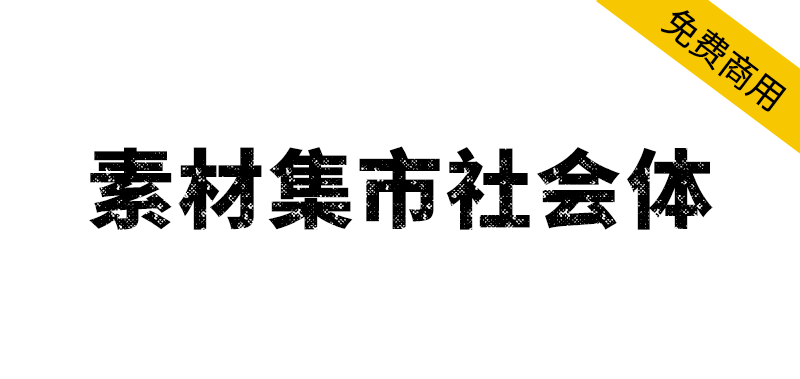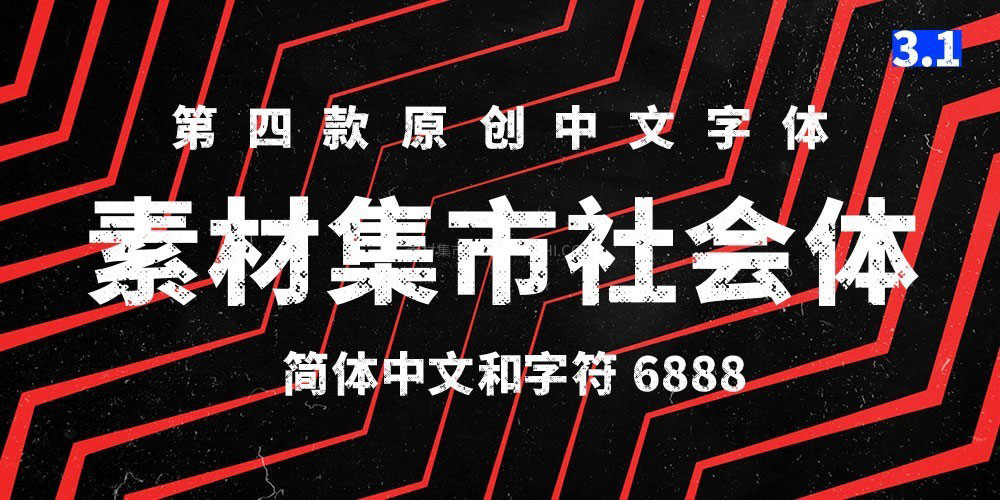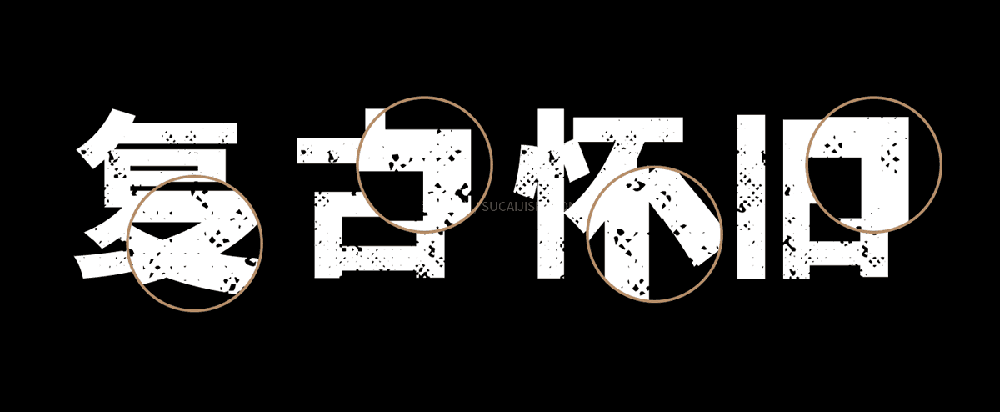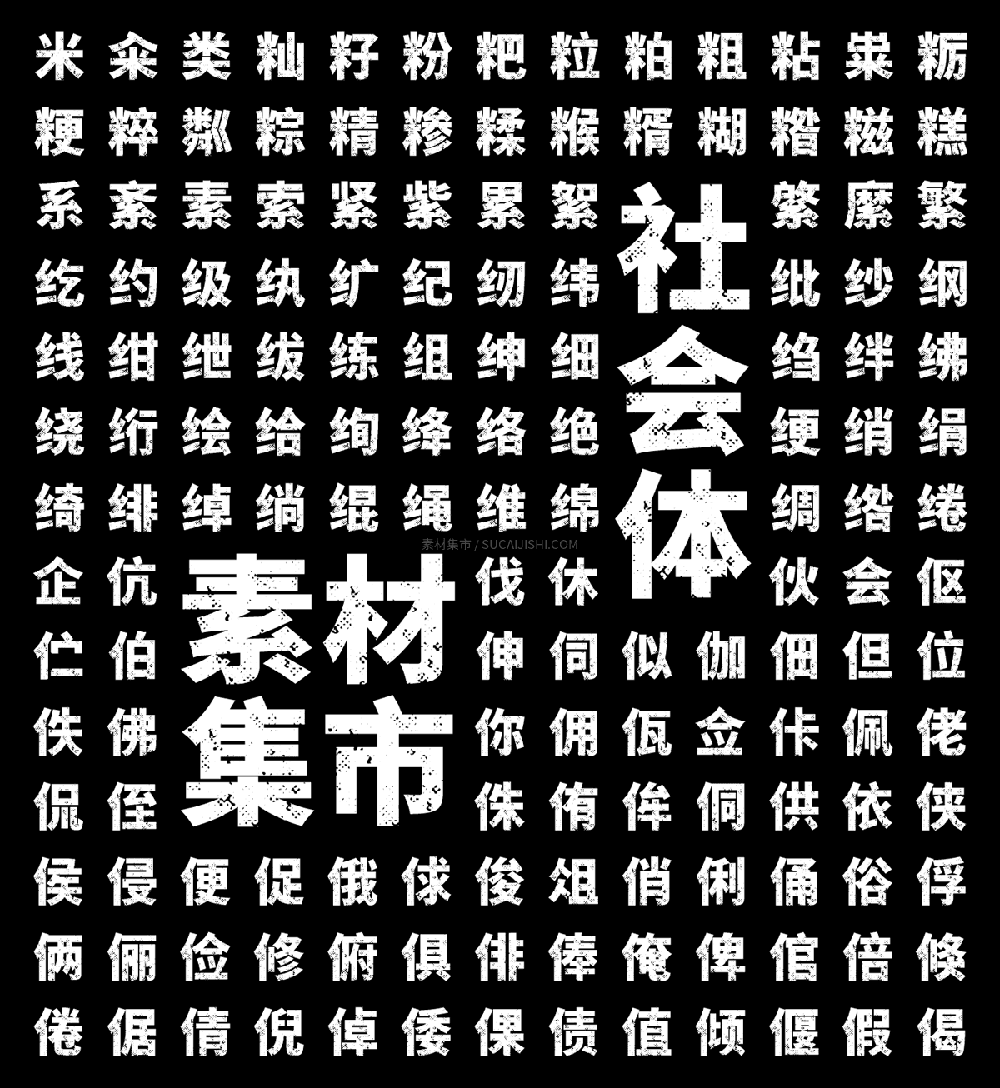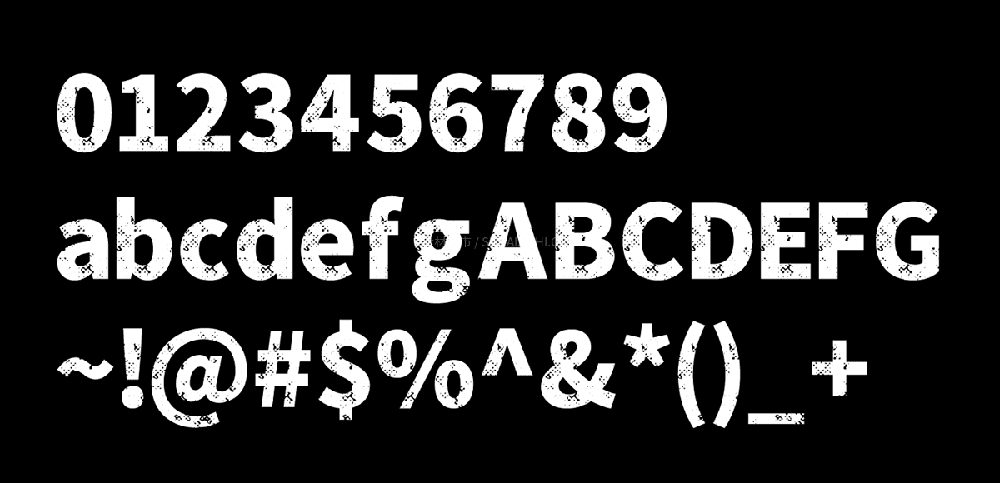
素材集市社会体是素材集市第四款原创字体「社会体」,由10名字集成员近4个月时间联合制作完成。作为各行业设计师,跨界完成一套字库,实属不易,感谢大伙的配合和支持。
字体介绍:一款基于思源黑体-Black字型上创建的字体,在不破坏原有字型的基础上,添加了破旧斑驳效果,独特的破旧字型充满复古怀旧风。字涵盖国家GB2312编码标准的6763个简体中文,加上英文、数字和符号共6888个字符。